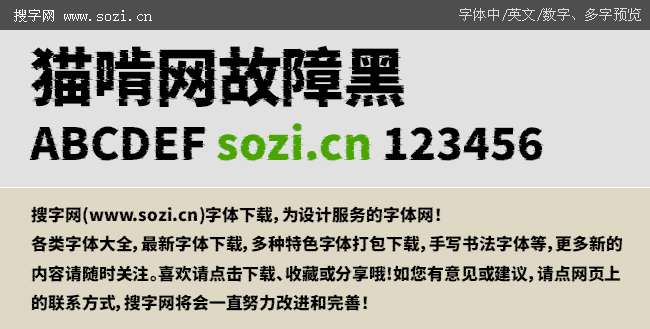
貓啃網(wǎng)故障黑
搜字網(wǎng)給大家提供一款貓啃網(wǎng)故障黑中文字體下載,貓啃網(wǎng)故障黑是一款藝術(shù)黑體字體,字體基于思源黑體CN改造,所以繼承了思源字體字?jǐn)?shù)滿的優(yōu)點(diǎn),用起來(lái)不用擔(dān)心缺字少字。支持免費(fèi)商用。適合應(yīng)用于藝術(shù)設(shè)計(jì)、平面宣傳設(shè)計(jì)、網(wǎng)頁(yè)設(shè)計(jì)、海報(bào)設(shè)計(jì)等應(yīng)用。